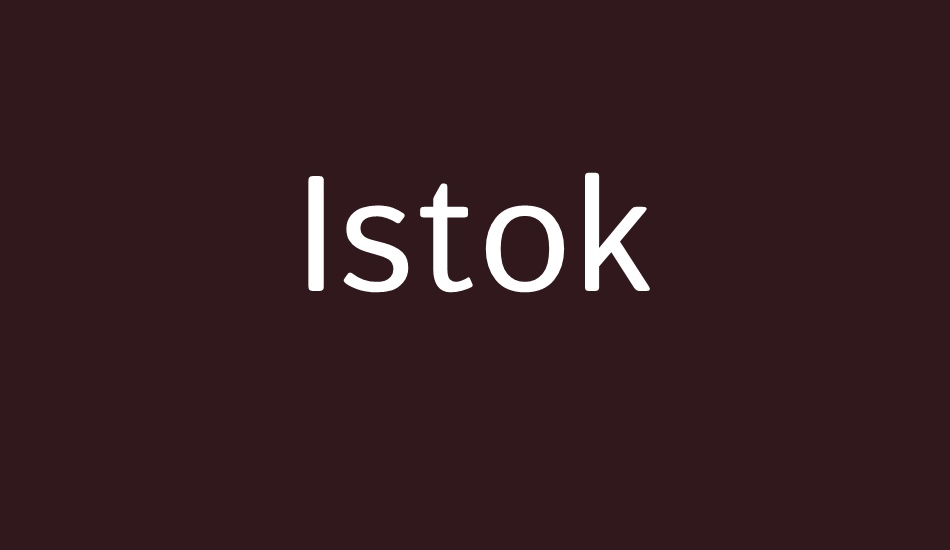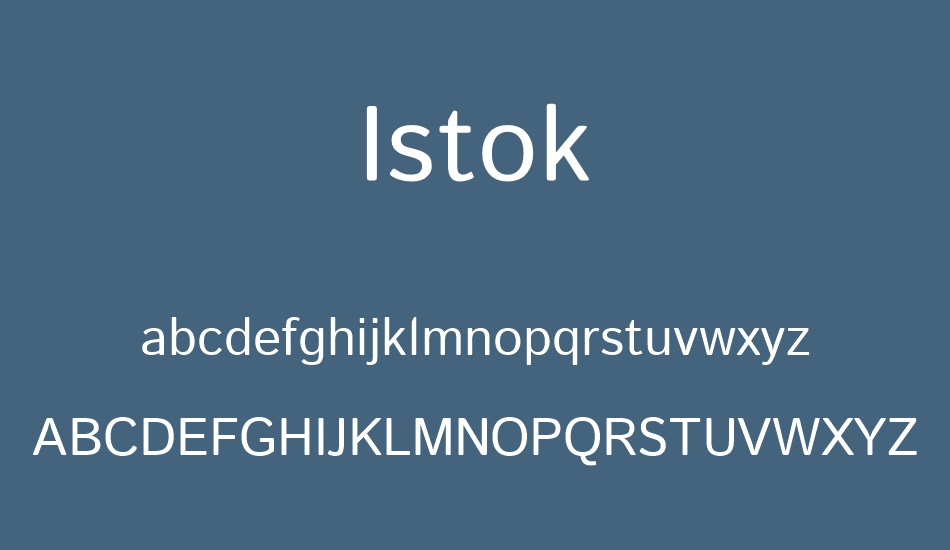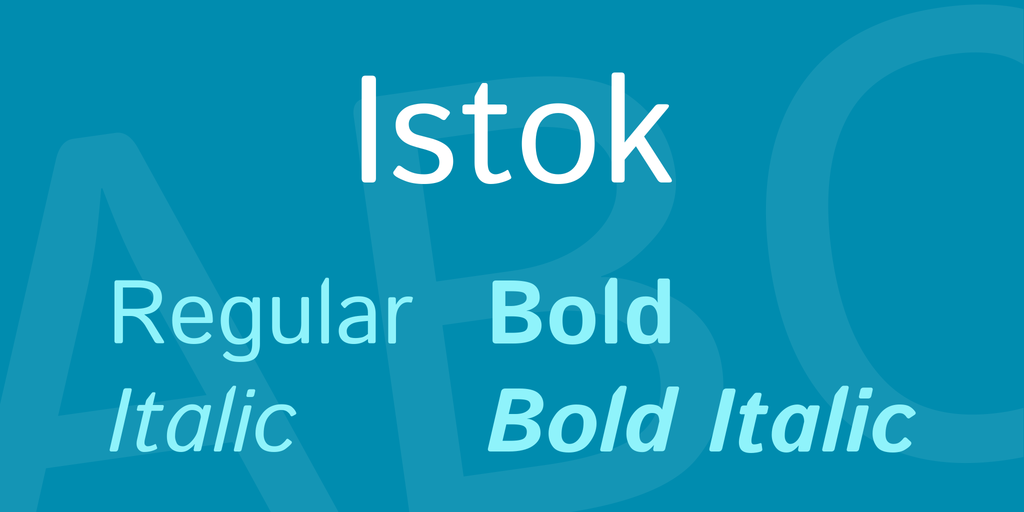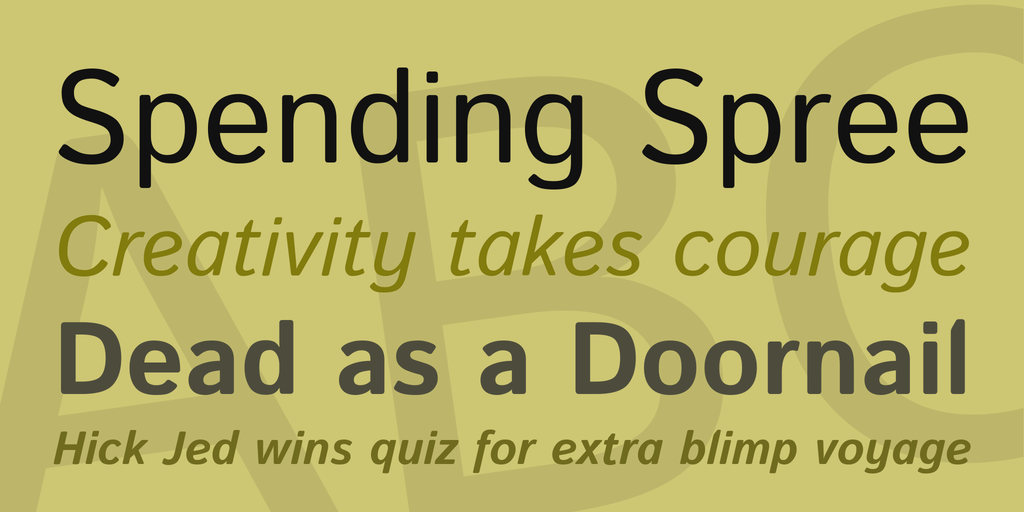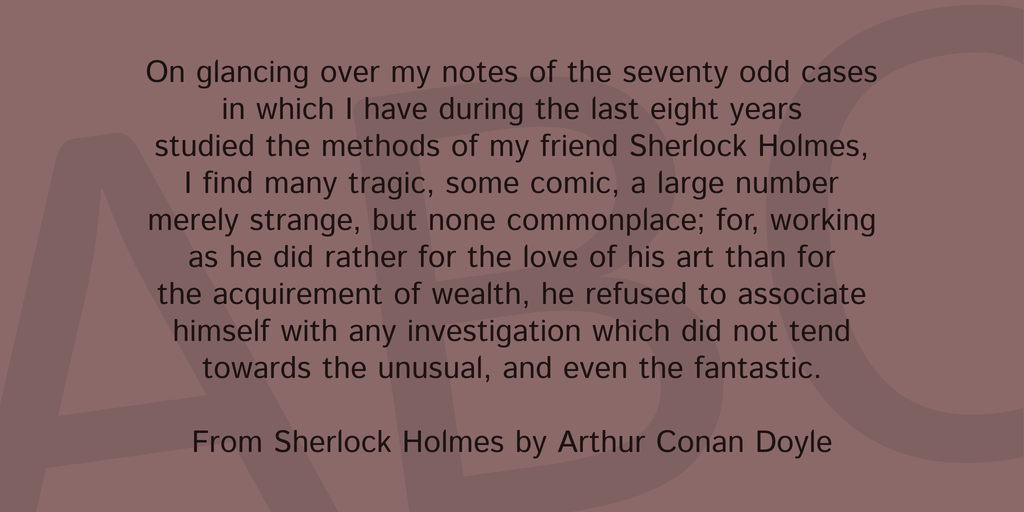
Istok font
Istok Web, 2008'den beri gelişmekte olan orijinal bir yazıdadır. İlk başta bazı temel harfler, TeX topluluğunun CM Bright font ailesinden özel olarak değiştirilmiş METAFONT kaynaklarına dayanmaktadır. (METAFONT çok esnek bir teknolojidir.) Fakat aslında Istok yazı tipleri bu kökenden çok uzaktadır. Yazı tipi konturları, serbestçe dağıtılabilir font editörü FontForge'da tasarlanmıştır.
Çoğu glif, LCD ekranlarda gösterilmek üzere manuel olarak ima edilir. TrueType yönergelerini programlamak için xgridfit'i bir araç olarak kullandım. Daha az sıklıkla kullanılan semboller, FontForge autohinting tarafından üretilen otomatik talimatlara sahiptir, elle ima yapılıncaya kadar. Manuel ve otomatik talimatların homojen görünmesi amaçlanmıştır.